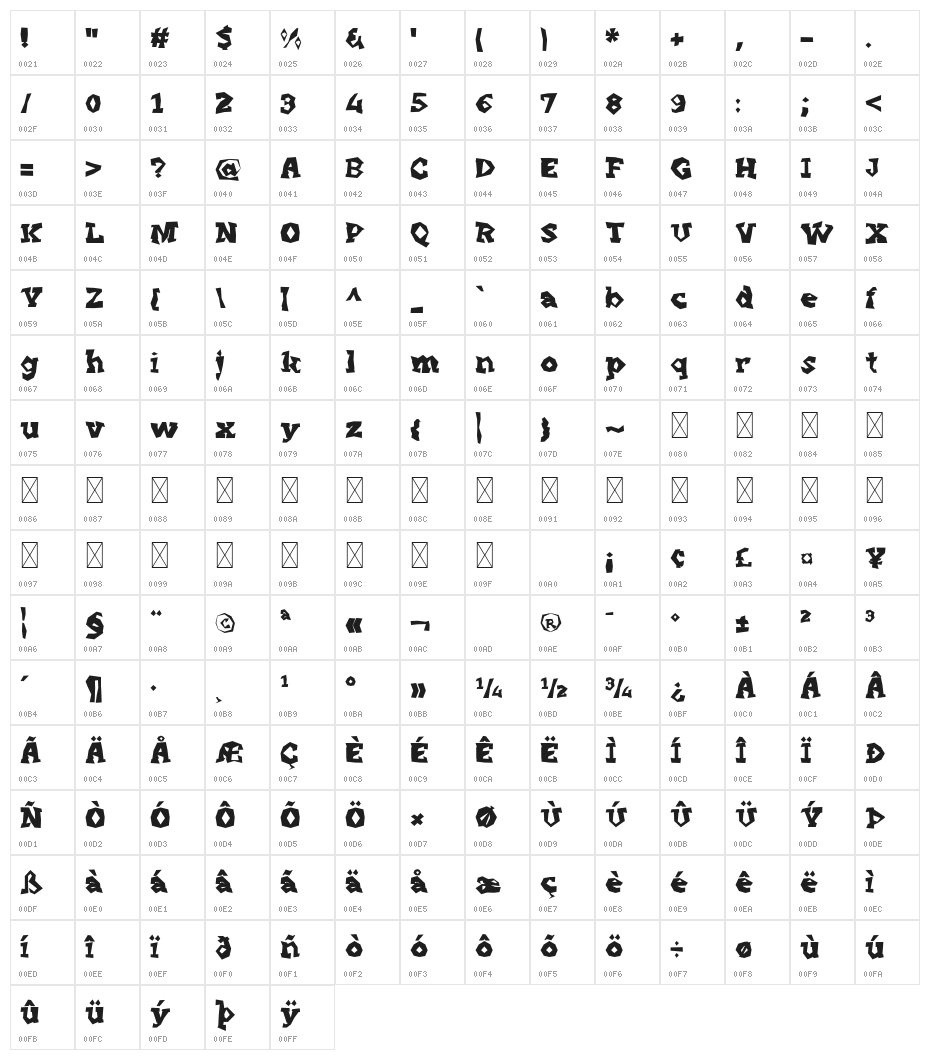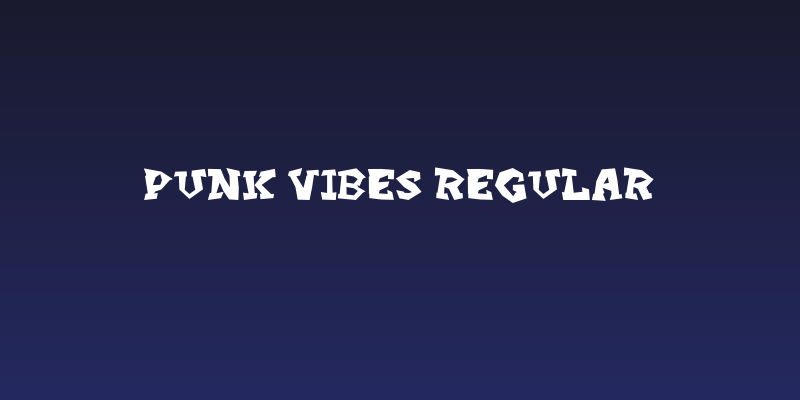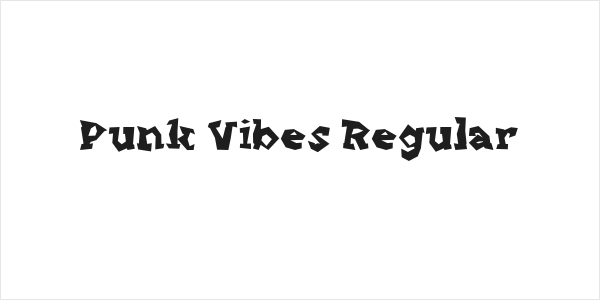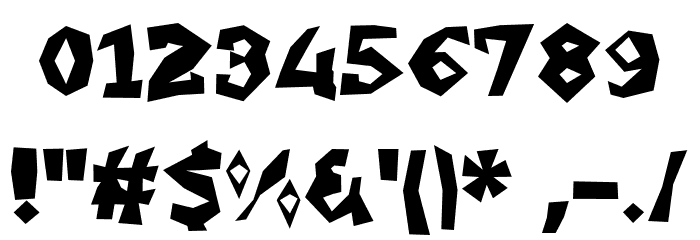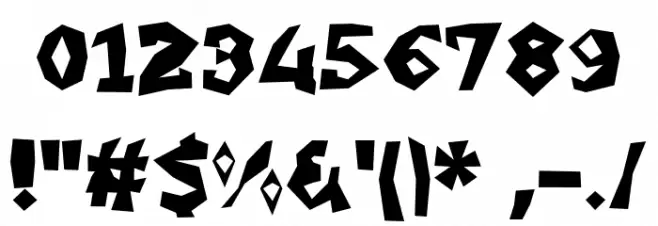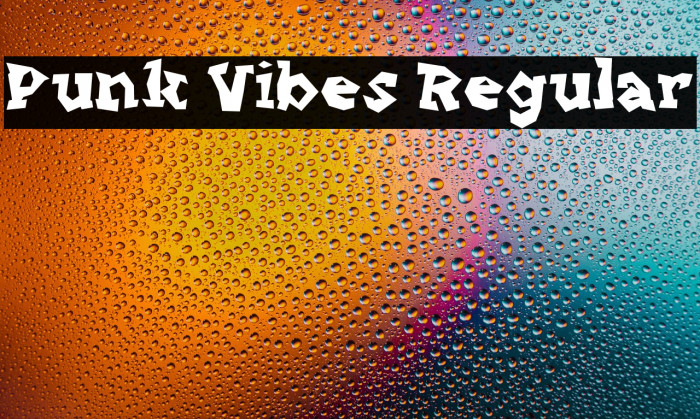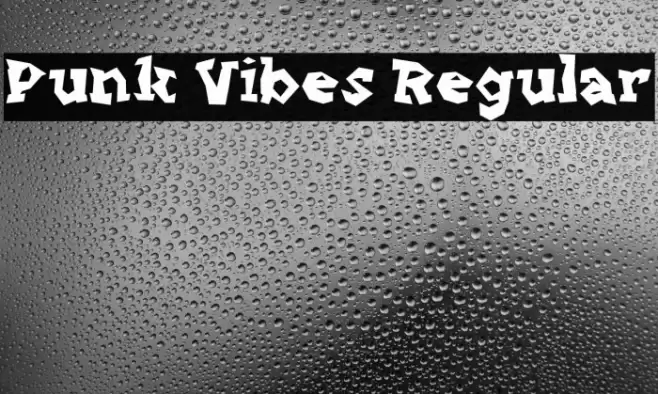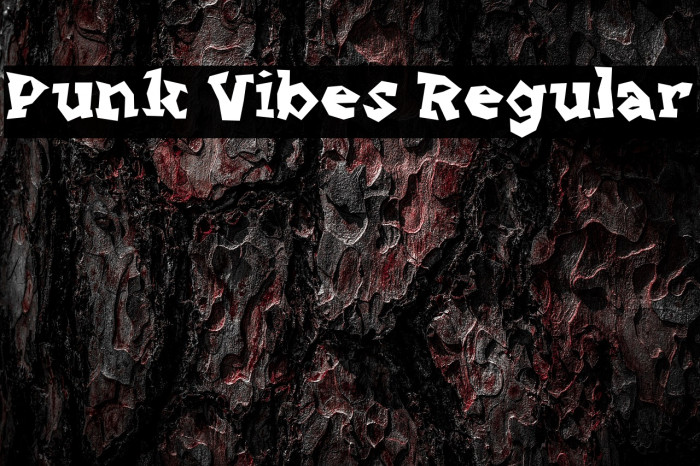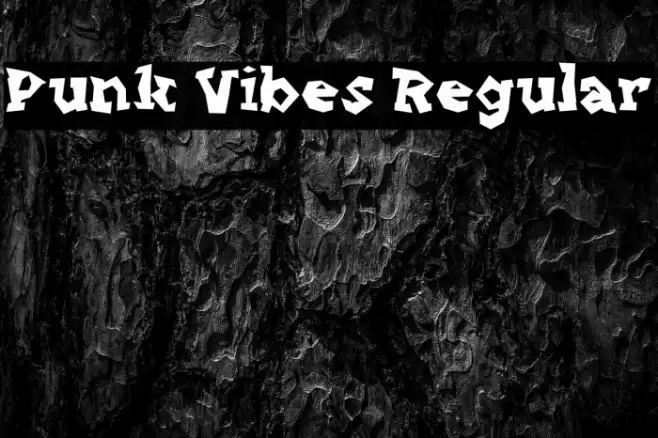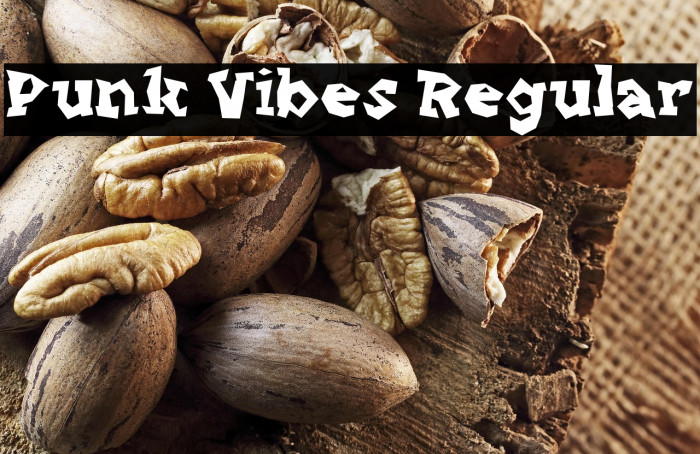
Punk Vibes Regular Font
| Gesamtstil | Punk, Edgy, Rebellious |
| Vorgeschlagene Projekte | Ideal for music album covers, concert posters, rebellious branding, and edgy graphic designs. |